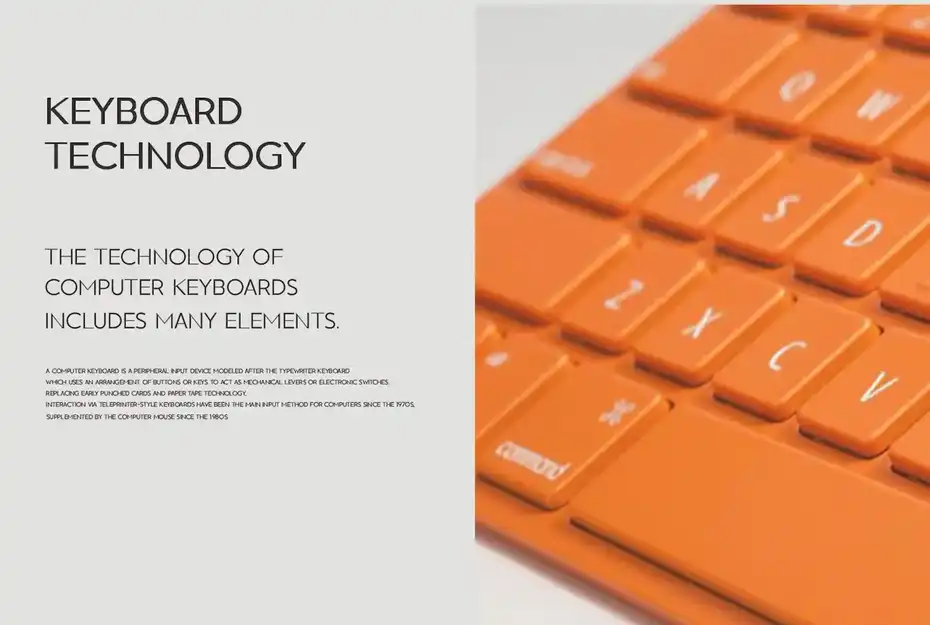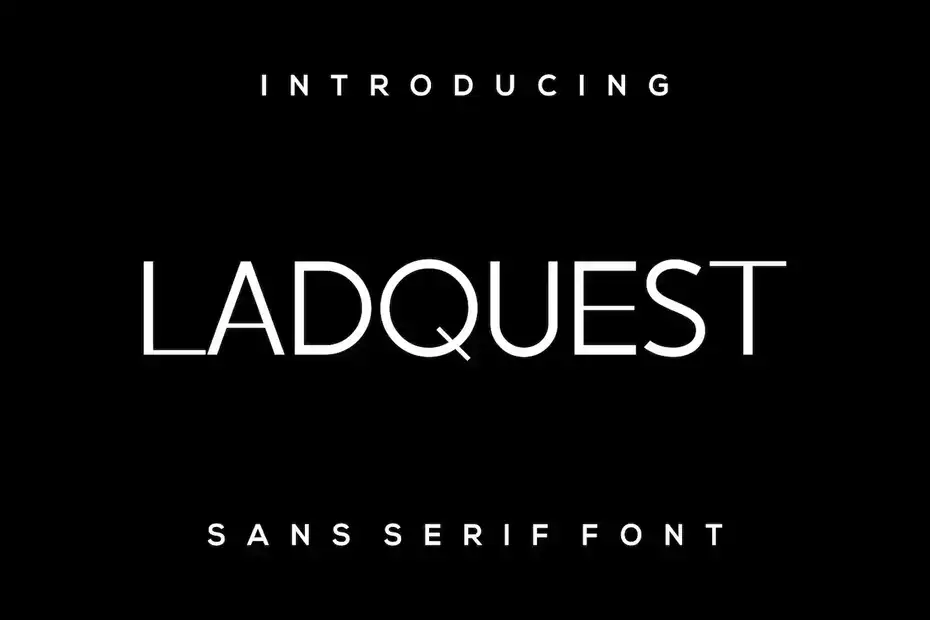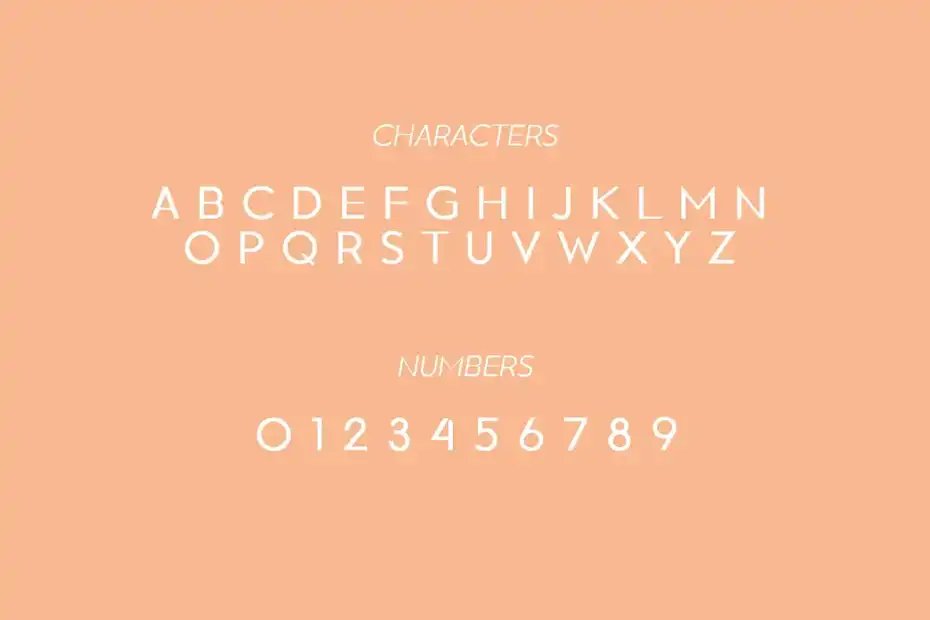
دانلود فونت انگلیسی مدرن Ladquest Font
فونت انگلیسی مدرن Ladquest Font : این مجموعه شامل فونت انگلیسی مدرن است که برای کتاب‌ های الکترونیکی، اپلیکیشن موبایل، سرفصل‌، بنر، پوستر، وب‌ سایت‌، مجلات و غیره مناسب میباشد.
• فضا بین حروف: معمولی، متراکم، با فاصله